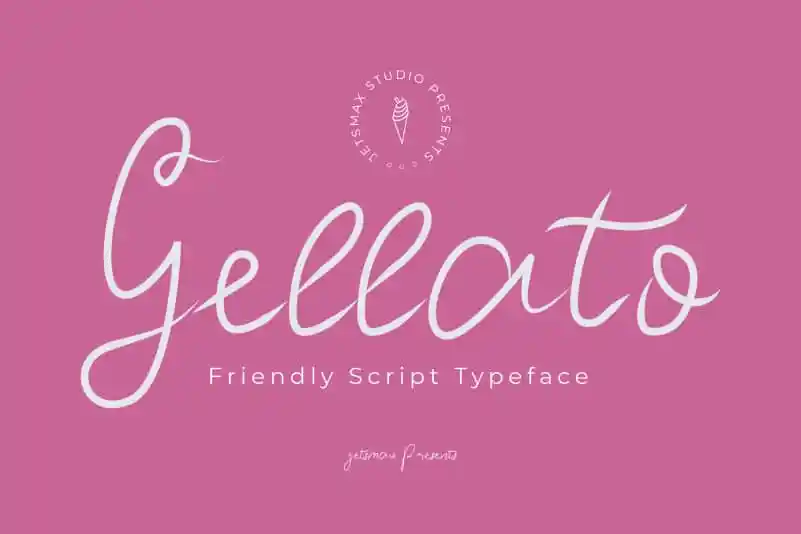
Gellato Script Font – Fonte Grátis
Gellato Script Font
A Gellato Script Font traz um sabor irresistível inspirado no tradicional gelatão italiano, com uma curva de tipo que segue fielmente a forma do recheio de um sorvete enchendo um cone. Esta fonte script proporcionará um toque autêntico e suave para qualquer projeto formal ou não-formal. Seja você um designer especializado ou um amante dos detalhes, essa fonte certamente irá agregar uma pitada extra de delícia à sua próxima criação gráfica. Seu designer, jetsmax, mantém a essência do gelatão em cada linha e curvatura, criando um design que vai desde o convencional até o sofisticado com elegância.